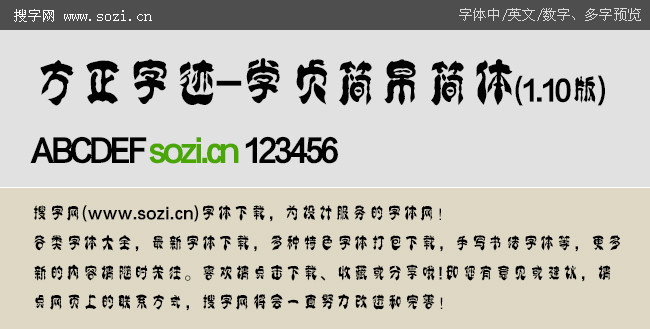
方正字跡-學(xué)貞簡(jiǎn)帛簡(jiǎn)體
搜字網(wǎng)提供一款方正字跡-學(xué)貞簡(jiǎn)帛簡(jiǎn)體中文字體下載,方正字跡-學(xué)貞簡(jiǎn)帛簡(jiǎn)體是方正字庫(kù)創(chuàng)作的一款創(chuàng)意字體,該字體別具一格,流暢飄逸,將字體的點(diǎn)滑線融為一體,用弧線完成,字體圓潤(rùn)卻又帶有典雅之感。能夠適用于藝術(shù)設(shè)計(jì)、包裝印刷、書籍裝幀等應(yīng)用。(本字體為個(gè)人非商用版,如需要商用請(qǐng)聯(lián)系方正公司購(gòu)買版權(quán))